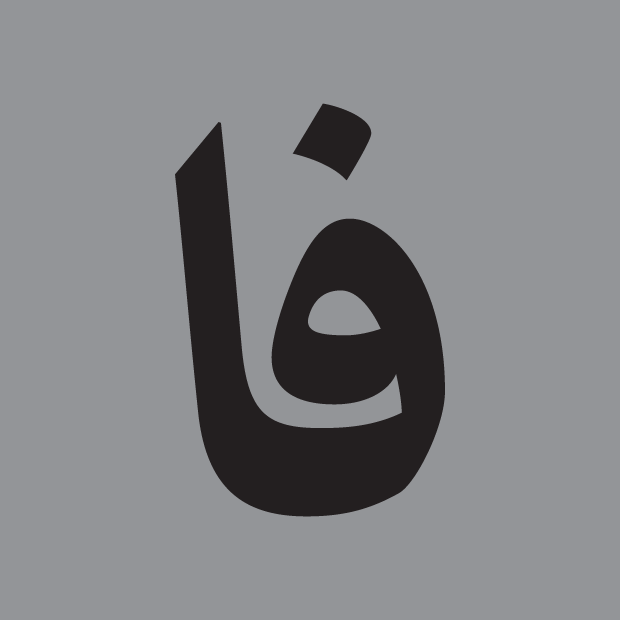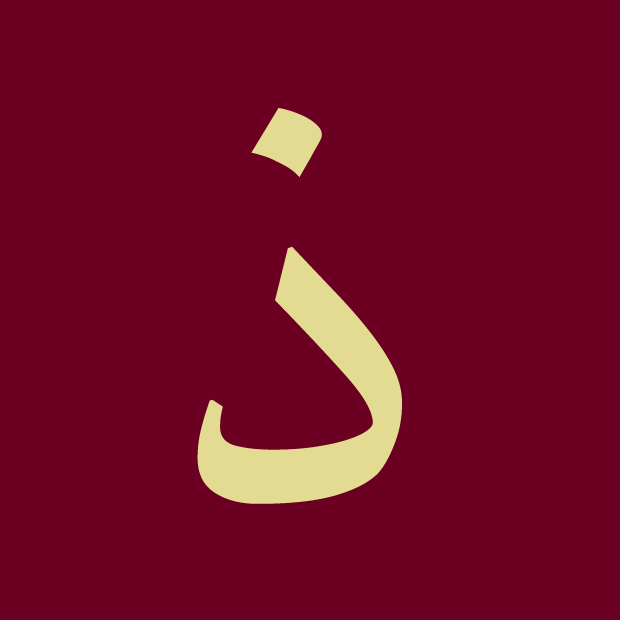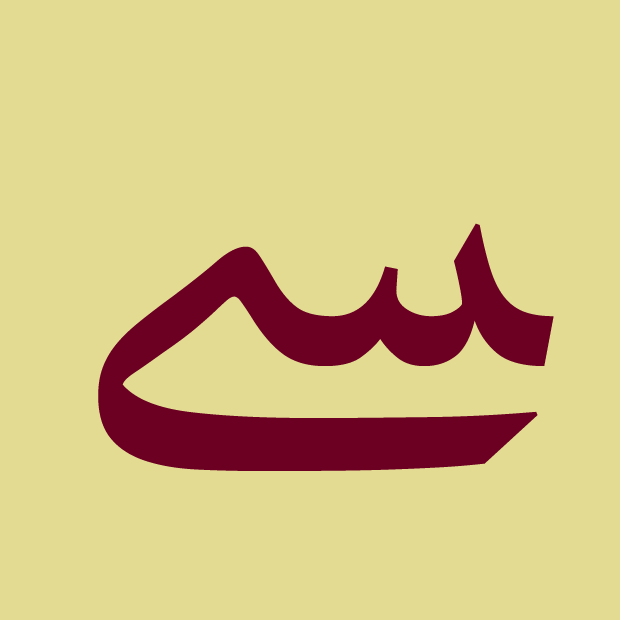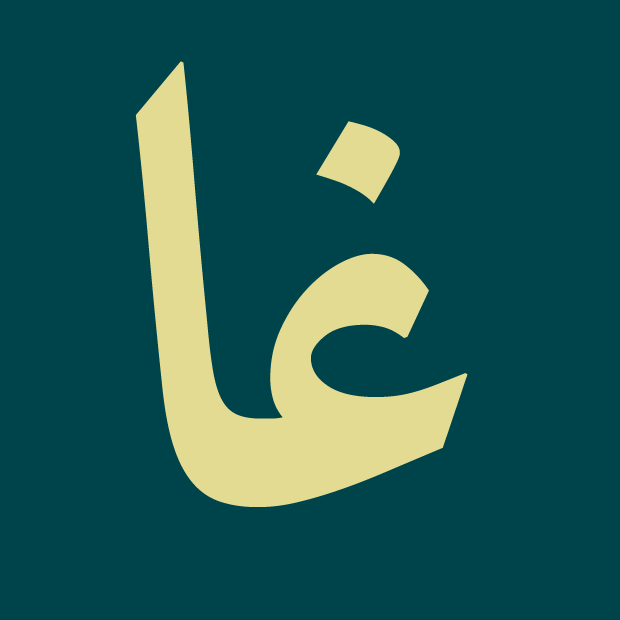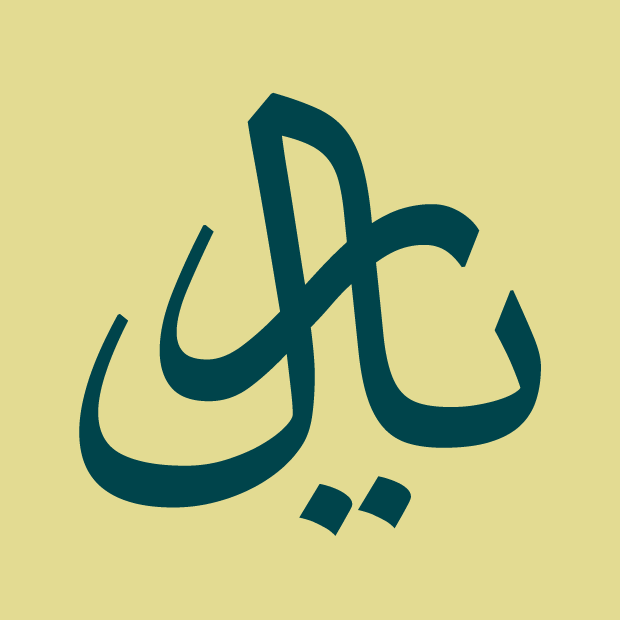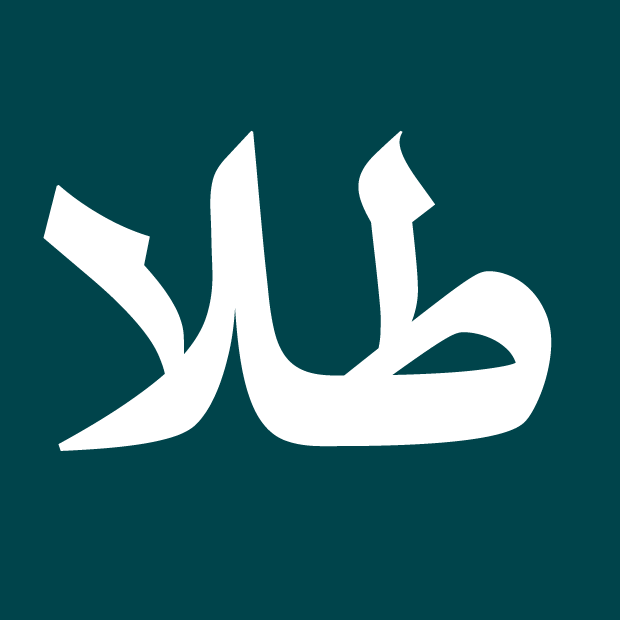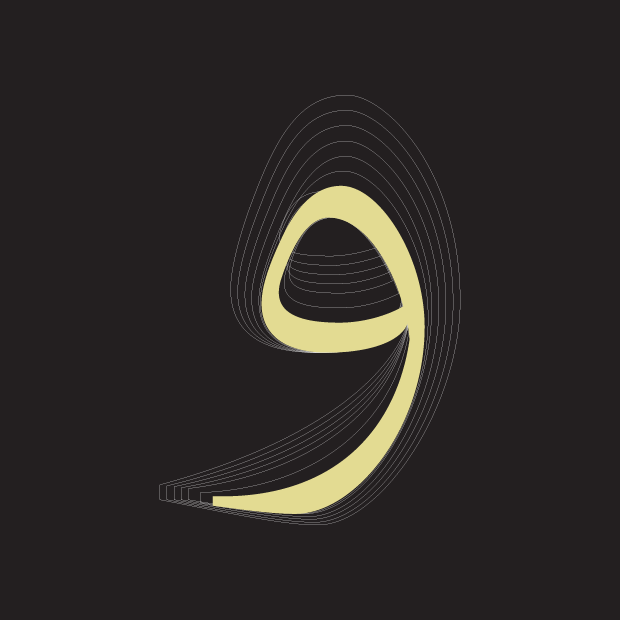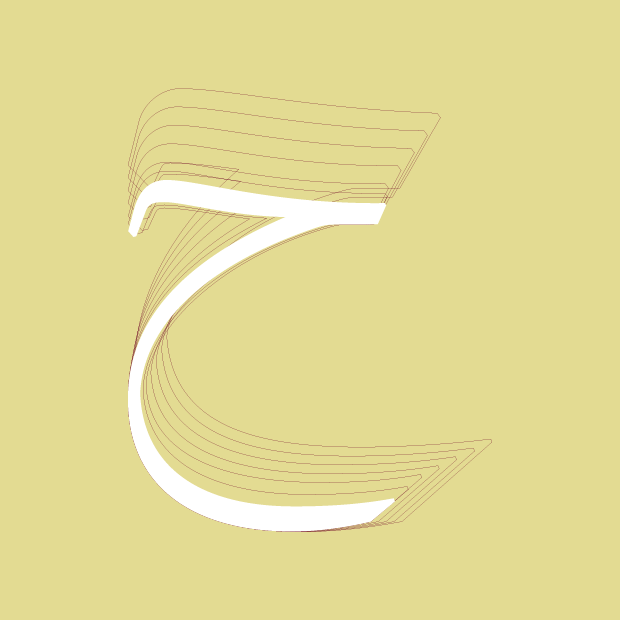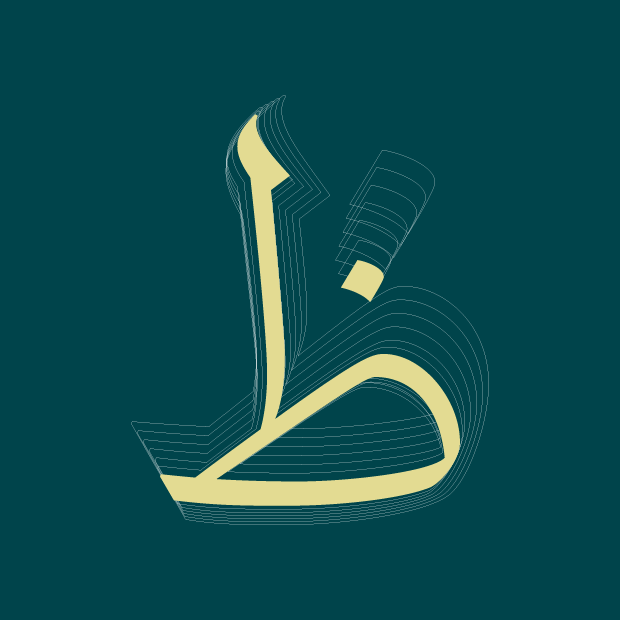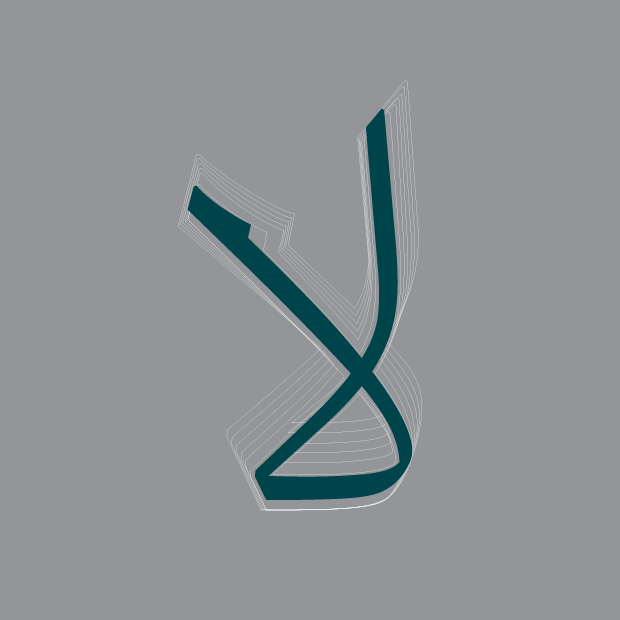
قلم آرامش font Aramesh
قلم آرامش
کاری از امید امامیان
درباره قلم آرامش
آرامش بر پایه خط نسخ و با هدف آفرینش تایپ‌فیسی ویژه‌ی متن طراحی شد. این تایپ نمی‌خواهد فریاد بزند بلکه خیلی آرام، با حفظ ویژگی‌های مثبت پیشینیان خود و در نظر گرفتن حافظه تصویری مخاطب از تایپ‌های متن قصد دارد تا مورد انتخاب جامعه ناشران و طراحان قرار گیرد. افرادی که در کنار تایپ‌های مدرن برای بدنه متن به تایپ‌های رسمی‌ و آشنا به چشمان مخاطب هم نیاز پیدا می‌کنند. حافظه تصویری زمانی اهمیت بیشتری پیدا می‌کند که سروکارمان با طراحی حروف متن باشد هر حرکت هیجانی می‌تواند باعث کند شدن روند خوانش و در نهایت منجر به انتقال ناقص مفهوم شود. تمرکز من در این مسیر بر حافظه تصویری مخاطب، اتصالات روان، فاصله‌گذاری منطقی، داشتن وزن‌های متنوع و حفظ کنتراست ضخامت بوده تا آرامش بتواند پاسخگوی همه‌ی نیاز‌های نوشتاری از جمله تیتر، سوتیتر و متن باشد.
امید امامیان
متولد ۱۳۶۸، کارشناس گرافیک و طراح تایپ ایرانی است، از سال ۱۳۹۱ فعالیت حرفه‌ای خود را در حوزه طراحی تایپ‌فیس آغاز کرده است. امید تاکنون فونت‌های متعددی را به صورت مستقل و یا در همکاری با طراحان مختلف مانند: رضا بختیاری‌فرد، مهدی ارشادی و کامیاب جعفری طراحی و توسعه داده است. از آثار او می‌توان به فونت‌های: جام‌جم، آرامش، واضح، دبستان، ری، ایرانسل، آریا، میکا و کمند اشاره کرد.
امید جوایز متعددی از جمله ۳ دوره نشان ممتاز تایپوگرافی TDC(۲۰۱۸ – ۲۰۱۹ و ۲۰۲۱) رتبه دوم و دیپلم افتخار گرانشان (۲۰۱۴ – ۲۰۱۷) و دیپلم افتخار سرو نقره‌ای ۱۳۹۶ را کسب کرده است.
او علاوه بر فعالیت حرفه‌ای، به عنوان مدرس در مدرسه دیزاین و ارتباطات ویژه و دانشگاه‌ سوره به تدریس طراحی تایپ مشغول است. وی همچنین کارگاه‌ها و سخنرانی‌های متعددی را در این زمینه برگزار و در نمایشگاه‌های داخلی و خارجی تایپ دیزاین شرکت داشته است.